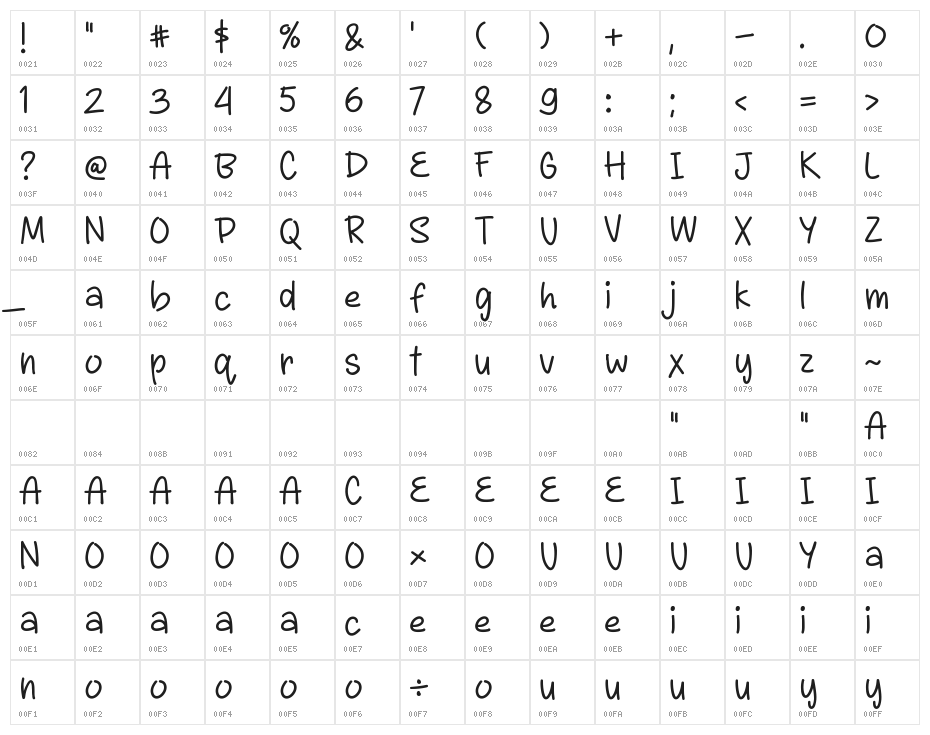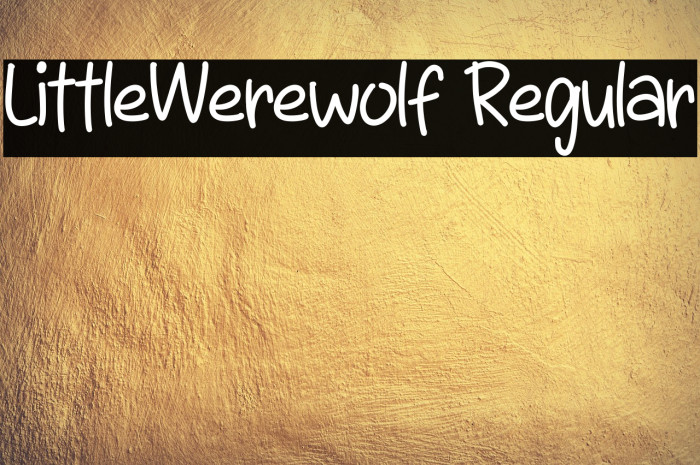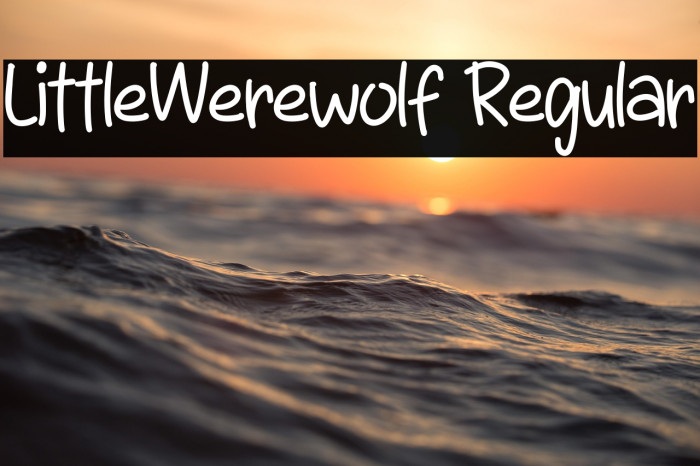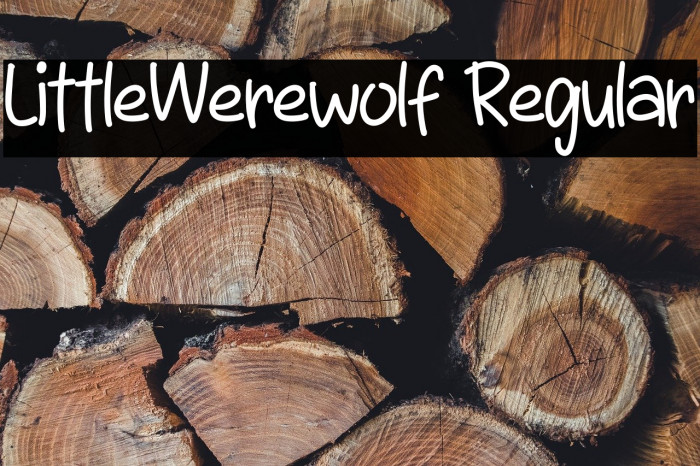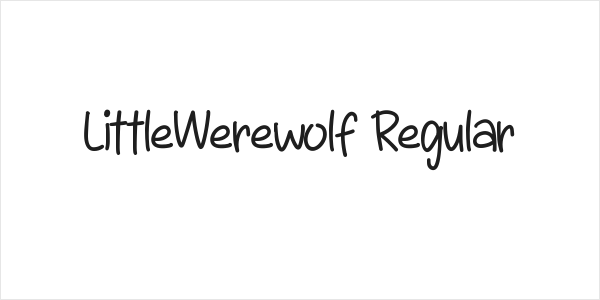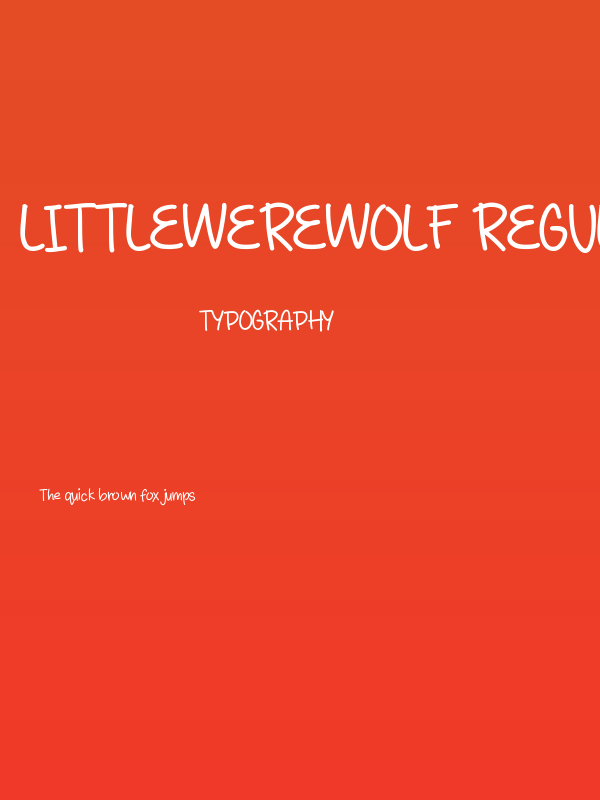
LittleWerewolf Regular Font
| Stile generale | Casual, Playful |
| Caso d'uso | Headlines, Informal text, Creative projects |
| Progetti proposti | Ideal for invitations, greeting cards, children's books, and informal branding. |